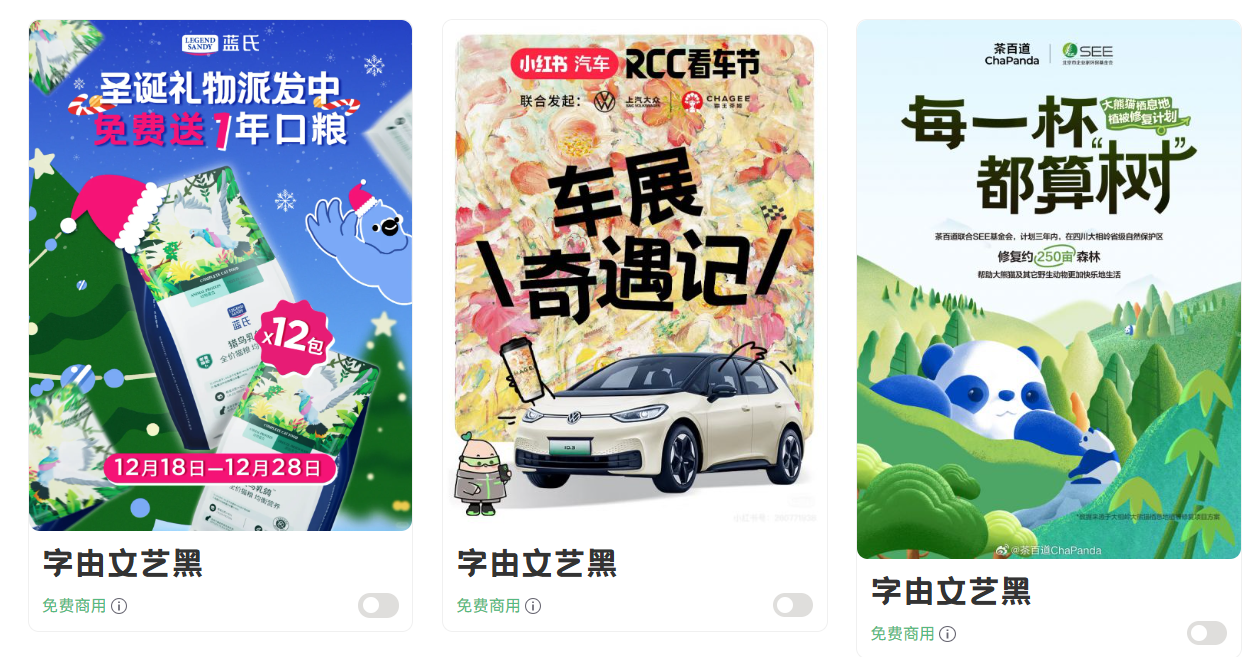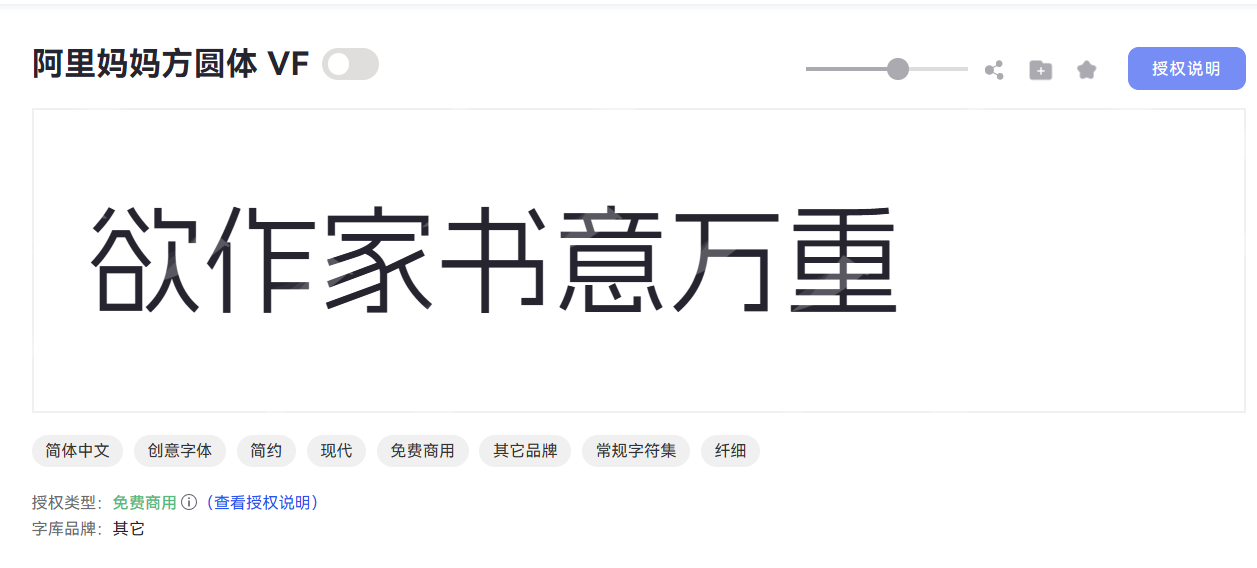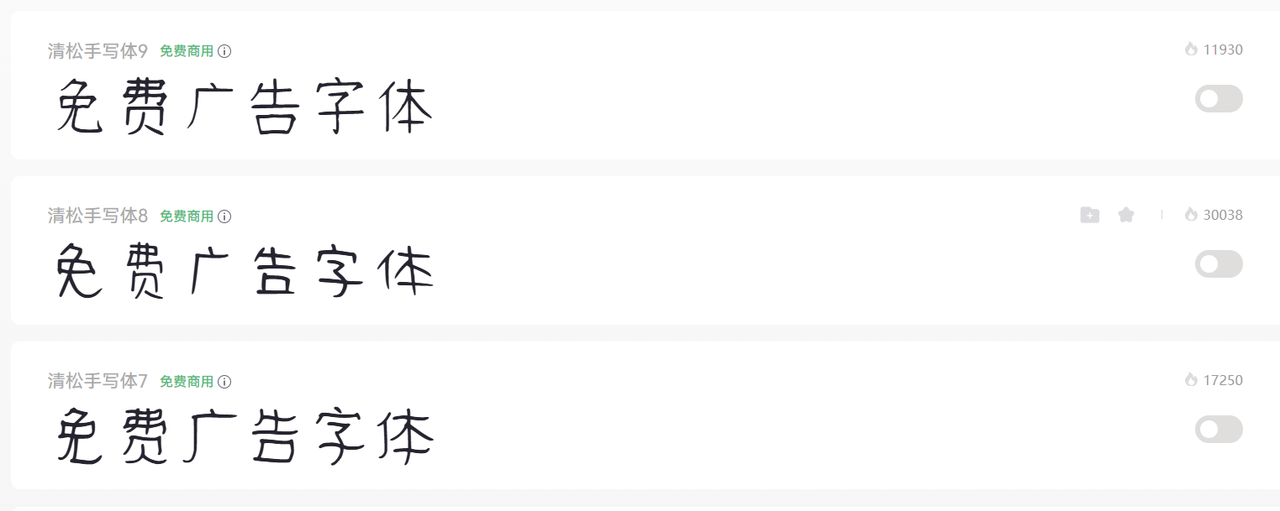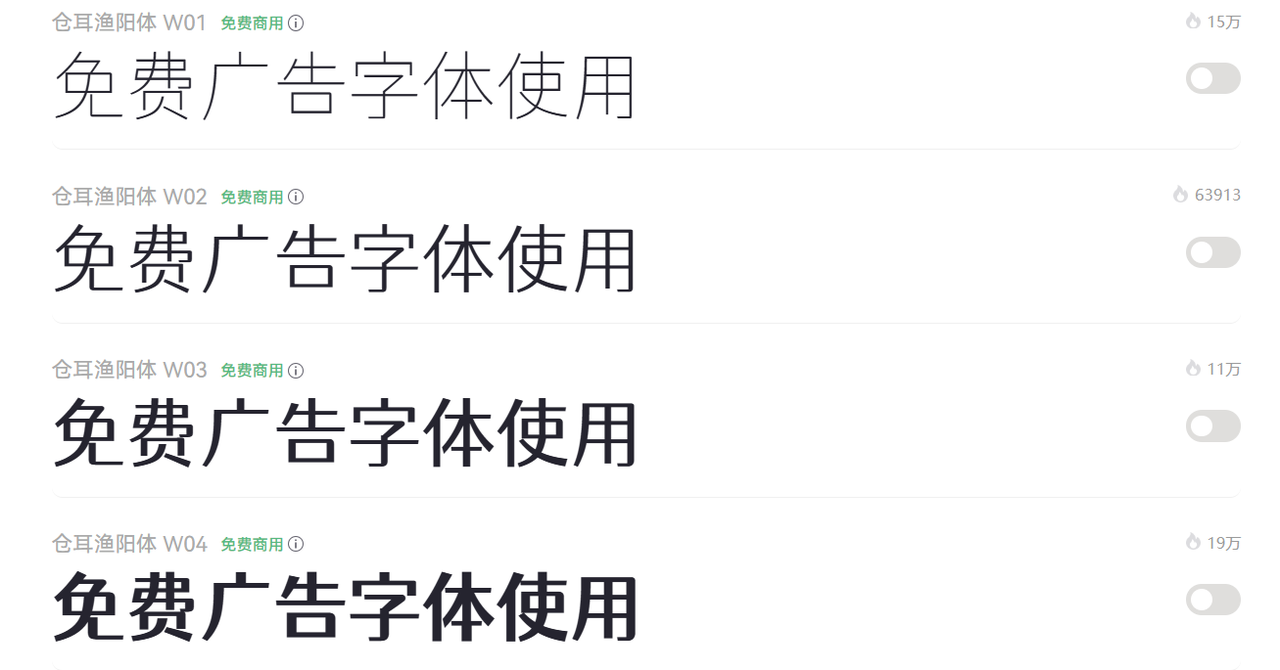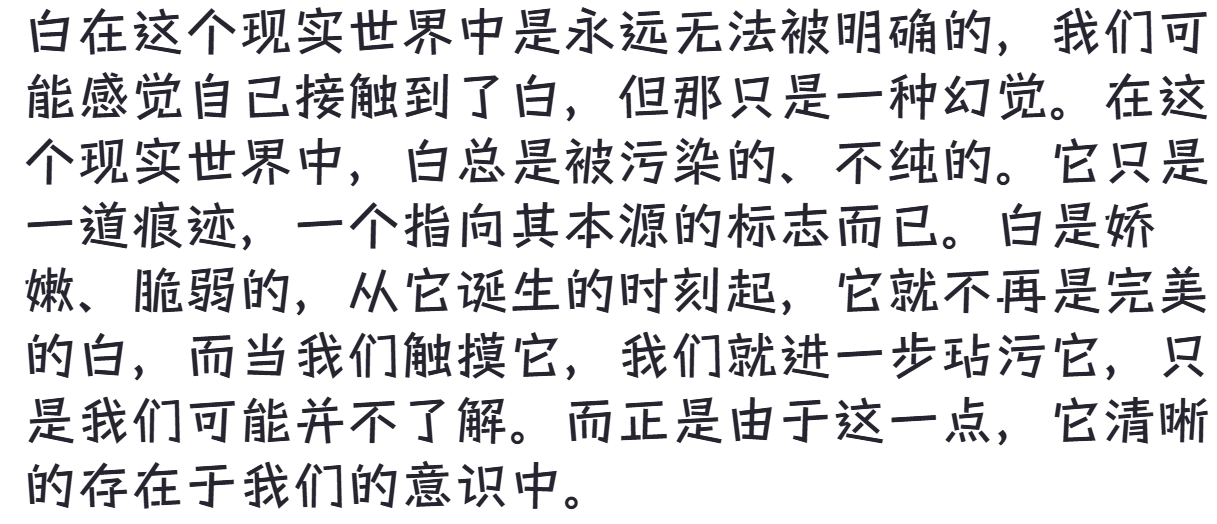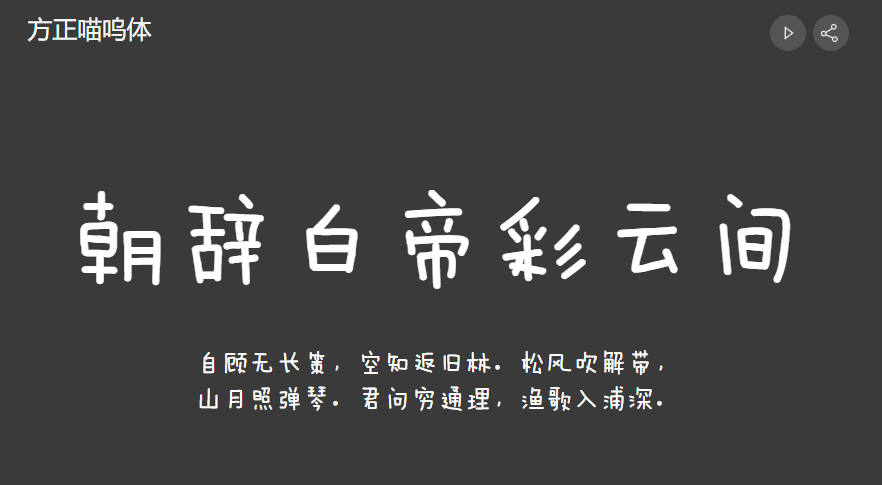
广告字体是免费字体吗?来看本文整理的免费广告字体
一、免费的广告字体推荐:
在广告场景中,字由文艺黑适合作为主标题或重点信息展示。它是一款适合广告视觉设计的现代黑体字体,整体字形简洁大方,同时加入了一些更具设计感的细节处理,让文字在保持清晰阅读的基础上拥有更丰富的视觉层次。
比如要设计品牌宣传海报、产品推广页面、活动主题时等,都可以通过字由文艺黑来提升画面的整体感。
阿里妈妈方圆体 VF
阿里妈妈方圆体 VF 是一款具有可变属性的创意字体,通过方形结构与圆润线条的结合,形成了更加柔和且富有现代感的视觉效果。实际使用时,它能适配不同风格的广告内容。无论是电商活动页面、新品推广素材,还是品牌营销海报,都可以根据画面需求调整字体呈现效果。
清松手写体
清松手写体采用自然流畅的手写风格,字体线条具有一定的随性感,能让广告文字呈现出更加轻松的视觉氛围。在一些注重情感表达的广告项目中,清松手写体能够发挥较好的作用。使用该款字体时,建议将它用于短标题、宣传语或重点文案区域。由于字体个性较明显,大量文字排版可能会影响整体阅读效果。
仓耳渔阳体
仓耳渔阳体是一款具有东方气质的特色字体,字形设计融合了传统文字美感与现代视觉表现方式,能够为广告作品带来更加鲜明的风格特点。当设计作品需要体现地域文化或传统元素时,比如国风品牌推广、传统产品宣传、艺术展览活动以及特色餐饮广告等,可以将仓耳渔阳体作为标题字体使用,通过字体本身的风格强化广告主题,让视觉表达更加统一。
游趣体
游趣体是一款偏创意方向的字体,整体风格轻松活泼,字体造型带有一定的趣味性,更符合年轻化设计需求。这款字体的优势在于能够快速传递轻松的品牌感受,它适用于需要营造愉快氛围的场景,比如儿童用品宣传、潮流品牌推广、社交媒体营销图片等。当搭配插画、卡通元素或明快的视觉设计时,可以让广告内容更加贴近年轻用户群体。
方正喵呜体
方正喵呜体字形设计更加灵活,是一款具有可爱风格的创意字体,比较适合儿童产品、休闲食品、活动宣传以及创意周边设计等这样以年轻消费群体为主的广告内容。
在使用时,可以将方正喵呜体作为标题或装饰文字搭配使用,通过灵活字形增强广告的亲和力,让整体设计更加具有互动感,为广告画面增加轻松、有趣的视觉感受。